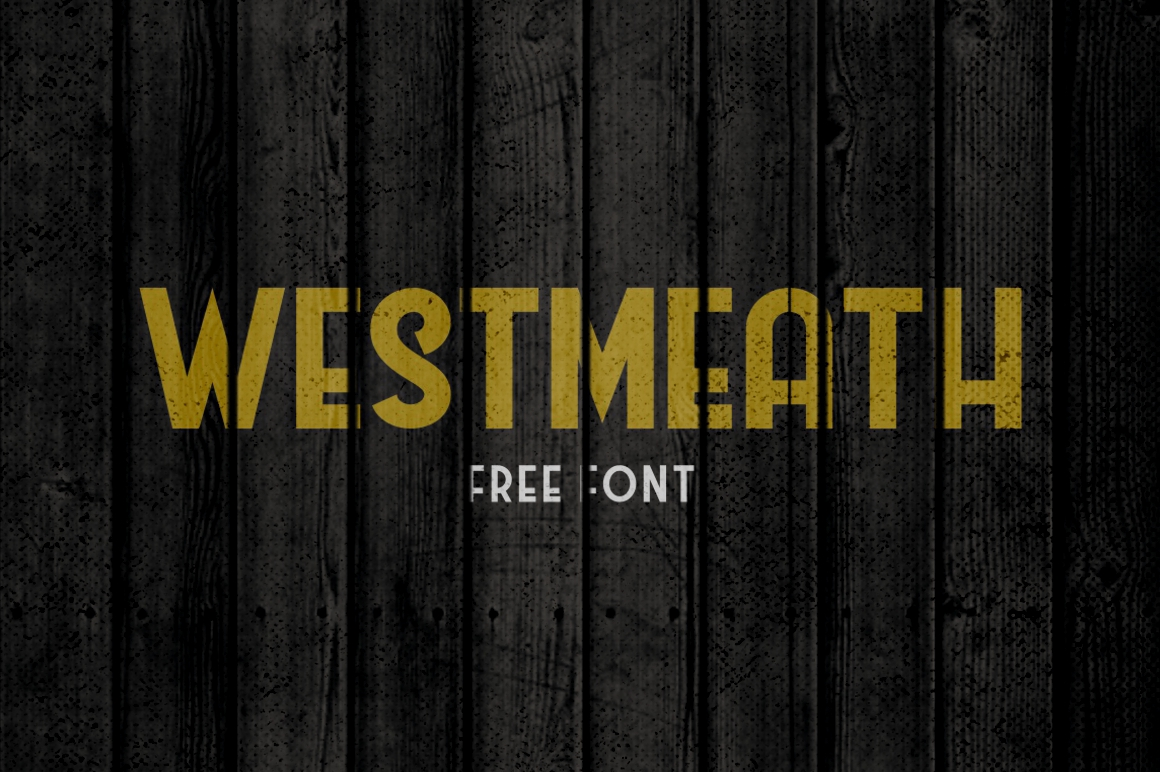
Westmeath Font é uma fonte sans-serif que traz uma nova ideia à categoria de fontes sem traço. Introduzida pela Twicolabs Design, esta fonte foi projetada pelo designer Hamilton e está totalmente disponível de graça. Westmeath apresenta um design limpo em formato de sans-serif, com um toque algo mais espesso do que o usual (embora acreditamos que ainda se destaque como sedutor), característica tipicamente associada ao estilo art-deco mas também àquela que combina elementos clássicos e até mesmo trendy. Oferecida em duas versões, Regular e Italic, Westmeath é uma fonte que busca capturar o essencial no design gráfico contemporâneo, sendo um excelente complemento para qualquer projeto de design, seja ele digital ou impresso.